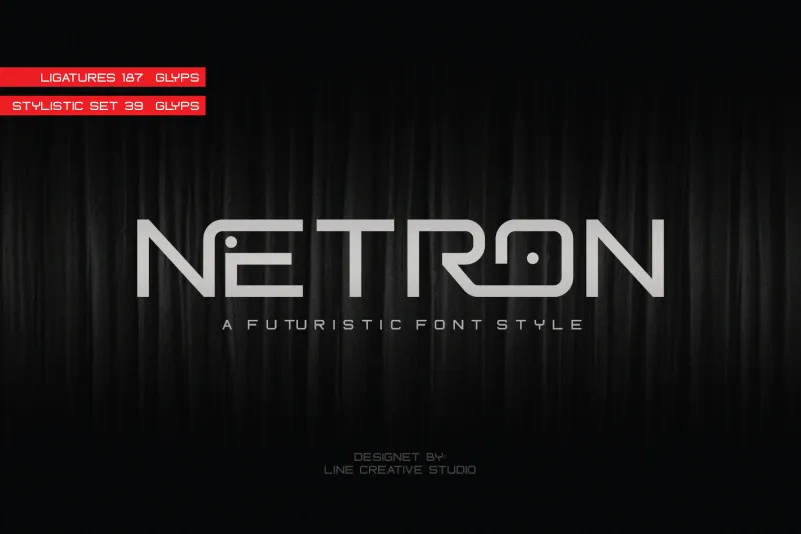
A Netron Font é uma escolha perfeita para qualquer projeto que busque uma sensação futurista com simplicidade criativa. Desenhada por Ari, esta fonte sans-serif é composta de linhas minimalistas, oferecendo um efeito moderno e inteligente a qualquer texto. Seu design prático se destaca especialmente em ambientes como posters, logotipos, revistas, capas, banners e até mesmo grandes obras de arte. A Netron Font inclui ligaturas e alternativas de letras que permitem uma personalização aprimorada dos textos, fazendo com que ela seja perfeita para trabalhos em alta escala. Seja você um designer de revistas ou um criador de logotipos, esta fonte será um complemento essencial para seu trabalho. O uso desta fonte não apenas adicionará uma identidade visual única a seus projetos digitais e impressos, mas também dará sua marca um toque sofisticado e moderno. Com as suas linhas limpas e minimalistas, a Netron Font é perfeita para aqueles que procuram uma fonte clara e direta que não cansa ao ser usada em longas faixetas de texto ou t-shirts com mensagens inspiradoras. Sua simplicidade permite que ela seja usada em diferentes ambientes sem perder sua essência futurista, tornando-a uma opção versátil e atraente para qualquer projeto.